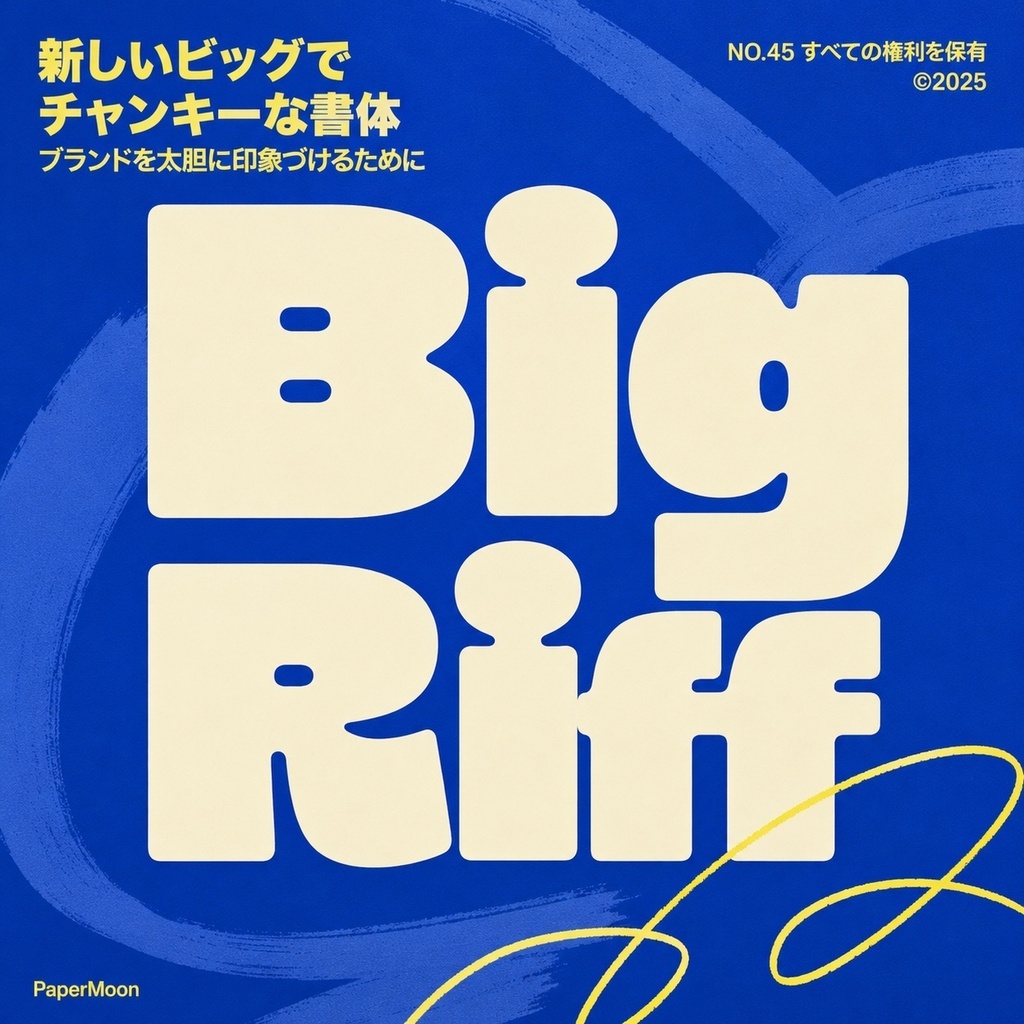
Big Riff | 太字ディスプレイ英字フォント | ロゴ・見出し・ポスター向け
Big Riff は、太字のディスプレイ英字フォントです。チャンキーな几何学的フォームと力強いウェイトで、大きなサイズで最大のインパクトを発揮します。角の丸みを帯びたモダンなプロポーションが、シンプルながらも存在感のあるタイポグラフィを実現します。 見出し・ポスター・ロゴ・ブランディングなど、短い文字列で強い印象を残したいデザインに最適です。Minimum Designムーブメントにも適合する、現代的なディスプレイ書体です。 収録内容 ・大文字 A–Z、小文字 a–z、数字、句読点(全392グリフ) ・OpenType Stylistic Alternates、Ligatures ・Kerning & Positioning(GPOS対応) 対応文字 ・Latin(欧文基本文字セット) 用途 ・ロゴ・ブランドアイデンティティ ・見出し・ポスタータイポグラフィ ・スポーツ・音楽・イベント用グラフィック ・パッケージ・ラベルデザイン ・SNS・サムネイル・動画タイトル ・ゲームタイトル・配信素材 形式 ・OTF(OpenType/CFF) ・TTF(TrueType) ・WOFF / WOFF2(Webフォント対応) 対応環境 ・Windows / macOS / Linux ・Photoshop、Illustrator、Figma、Canva 等の主要デザインツール ・Webブラウザ(WOFF2推奨) 利用許諾 ・Commercial Use バリアント:商用利用可(ビジネス、クライアント、広告、グッズ販売等) ・Personal Use バリアント:個人利用限定(自身の非商用プロジェクト、学習、練習等) ・再配布・販売・テンプレート埋め込み・フォントデータそのものの再販は禁止